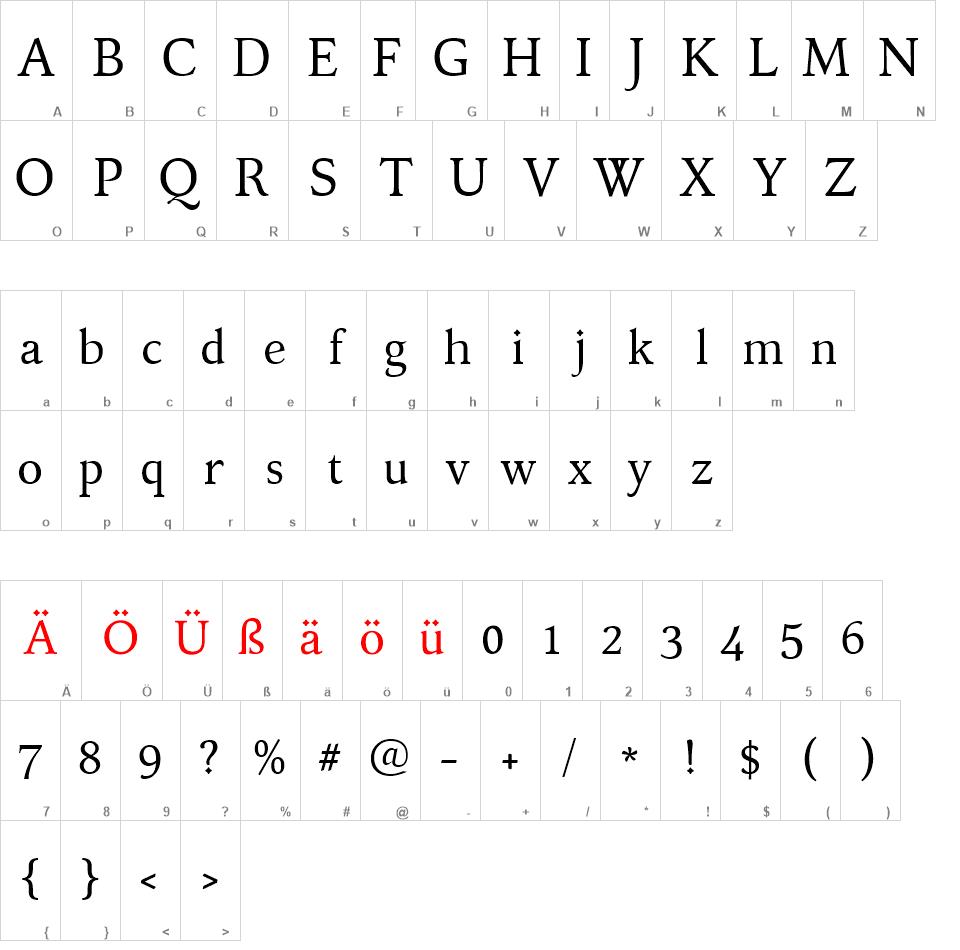
Obwohl Kelvinch für den Fließtext gedacht ist, habe ich mich bemüht, die Zeichen so ästhetisch ansprechend wie möglich zu gestalten, ohne das Ziel zu beeinträchtigen, in langen Texten bequem gelesen zu werden.
Es kommt in Regular, Italic, Bold und Bold Italic.
Es begann als meine eigene persönliche Schrift, aber irgendwann änderte sich das und andere Leute interessierten sich dafür und ich traf die Entscheidung zu versuchen, es gut genug zu machen, dass es mir nicht peinlich wäre zu wissen, dass andere Leute es benutzten. Ich habe nie darüber nachgedacht, es zu verkaufen.
Es umfasst viele Unicode-Blöcke, einschließlich Griechisch und Koptisch, Kyrillisch, Georgisch, Armenisch, Mathematische Operatoren, Verschiedene Symbole, Dingbats, Runen, Buchstabenähnliche Symbole, Pfeile und eine umfassende Abdeckung der meisten lateinischen Blöcke.
Es hat über ein Jahr gedauert, um sich zu entwickeln.